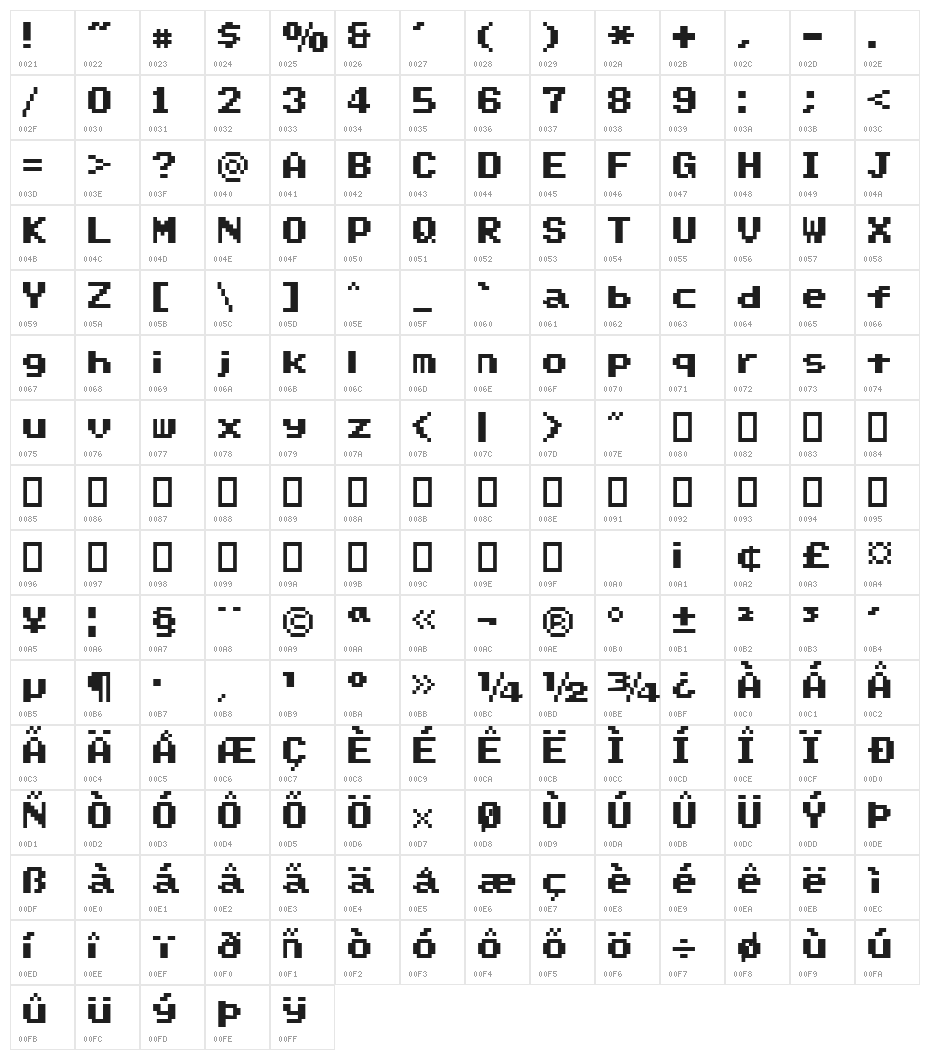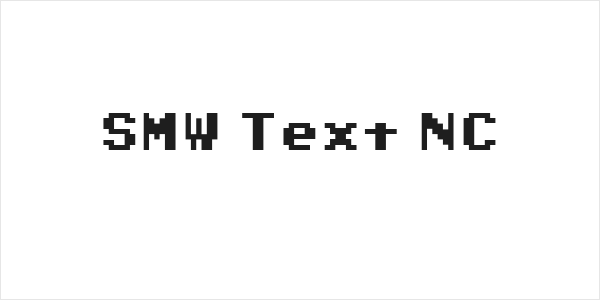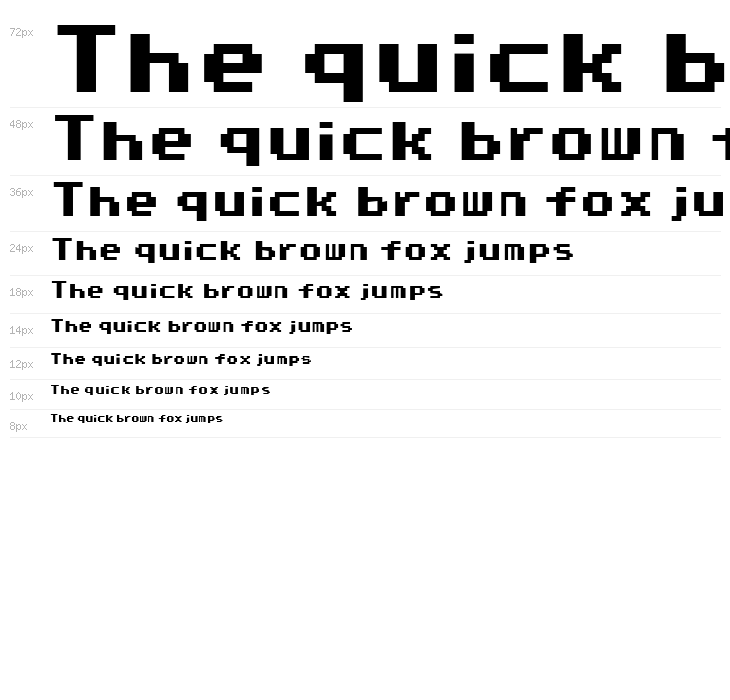
SMW Text NC Font
| Stile generale | Retro, Digital |
| Caso d'uso | Headlines, Logos, Digital Art |
| Progetti proposti | Ideal for video game design, retro-themed posters, digital art projects, and any creative work that seeks to evoke a sense of nostalgia for early computing. |